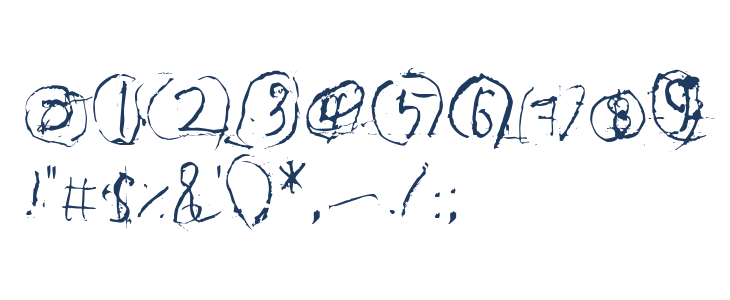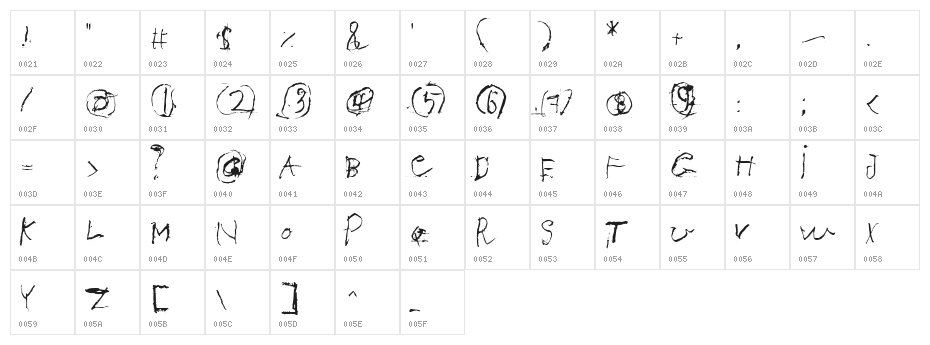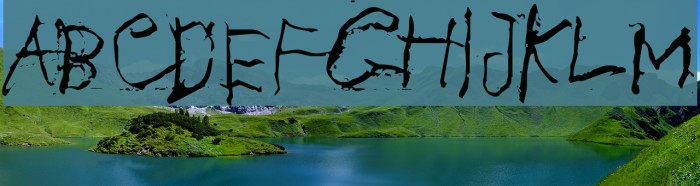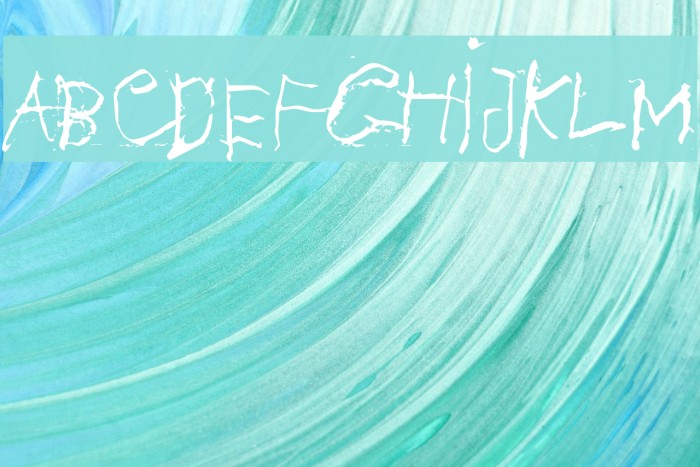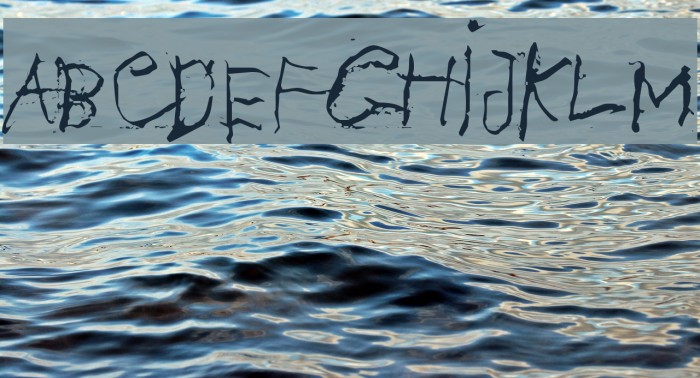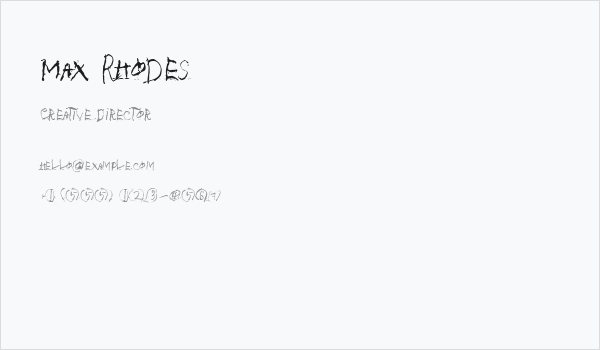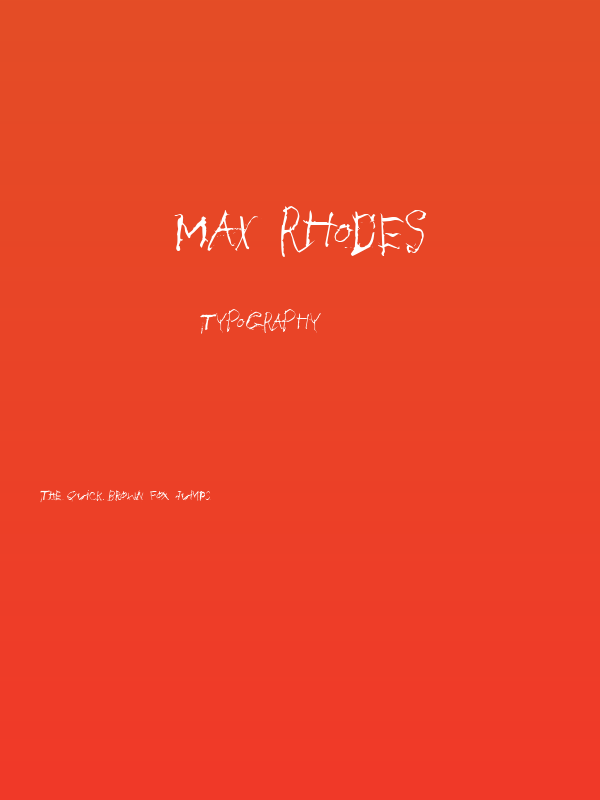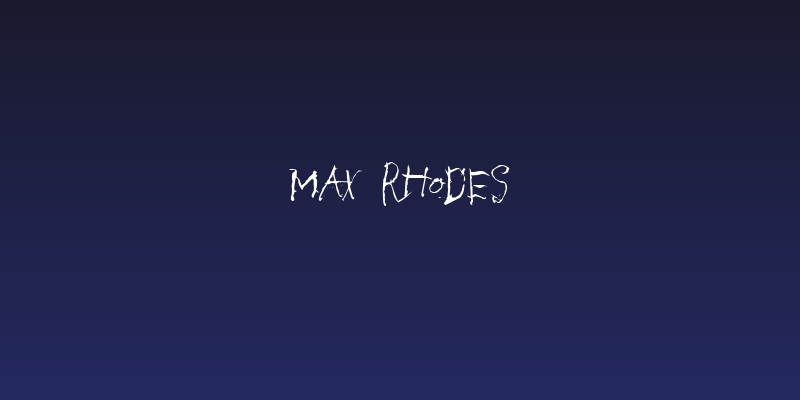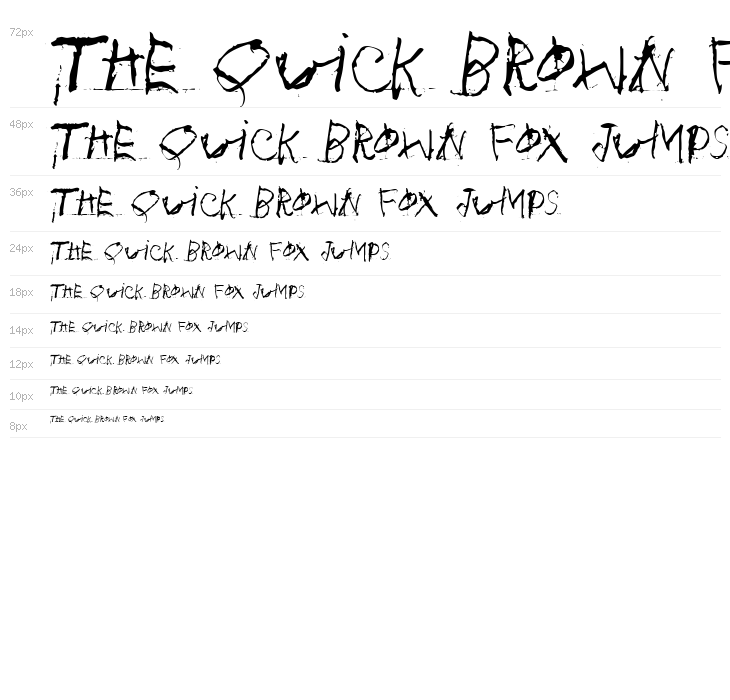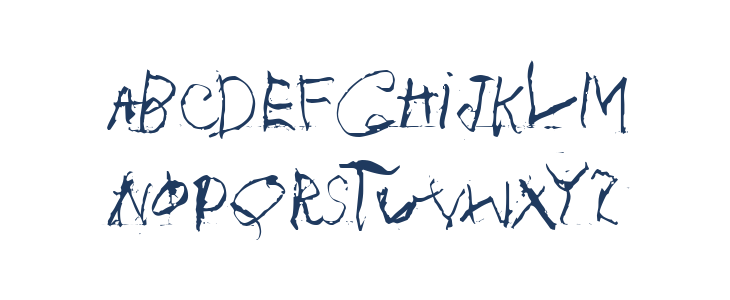
Max Rhodes Font
✎ Decorative
| حالة الاستخدام | Logos, Headlines, Artistic projects |
| مشاريع مقترحة | Ideal for album covers, artistic posters, creative branding, and any project seeking a bold, unconventional look. |